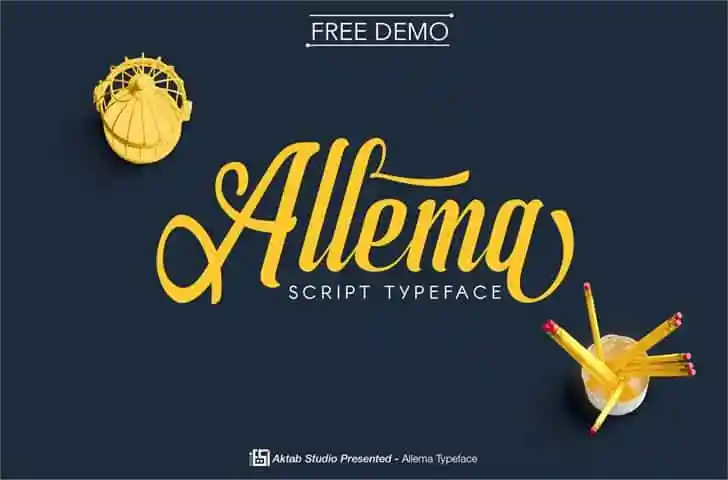
Allema Font – Download Grátis
Avejante nova descoberta no mundo das fóntes tipográficas é a Allema Script Font, apresentada pela Aktabstudio. Esta nova adição à biblioteca de tipos de letras moderna é uma obra-prima do estilo Calligráfico. Designado para aqueles que buscam um equilíbrio perfeito entre o tradicional e o moderno, esta fóntes vem com 1000+ traços e características únicas. A designação pela Aktabstudio tem como inspiração a arte da escrita à mão, refletindo em formas únicas de calligráfico que exalam sofisticação. Com uma escrita macia e elegante, esta fonte é perfeitamente adequada para um trabalho moderno que valoriza o estilo e a qualidade dos traços. A Allema Script é uma verdadeira joia da arte tipográfica, tornando-se uma ótima opção para designers e artistas digitais em busca de expressar seus trabalhos de forma única e sofisticada.